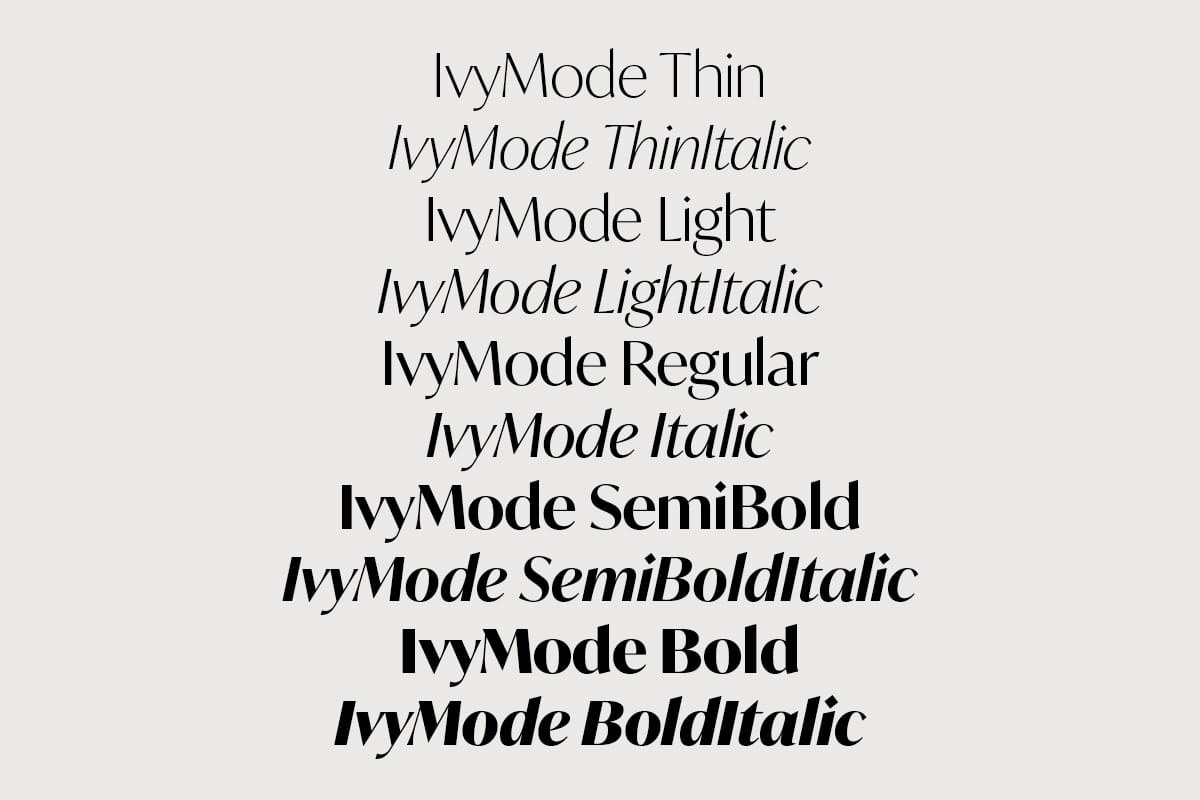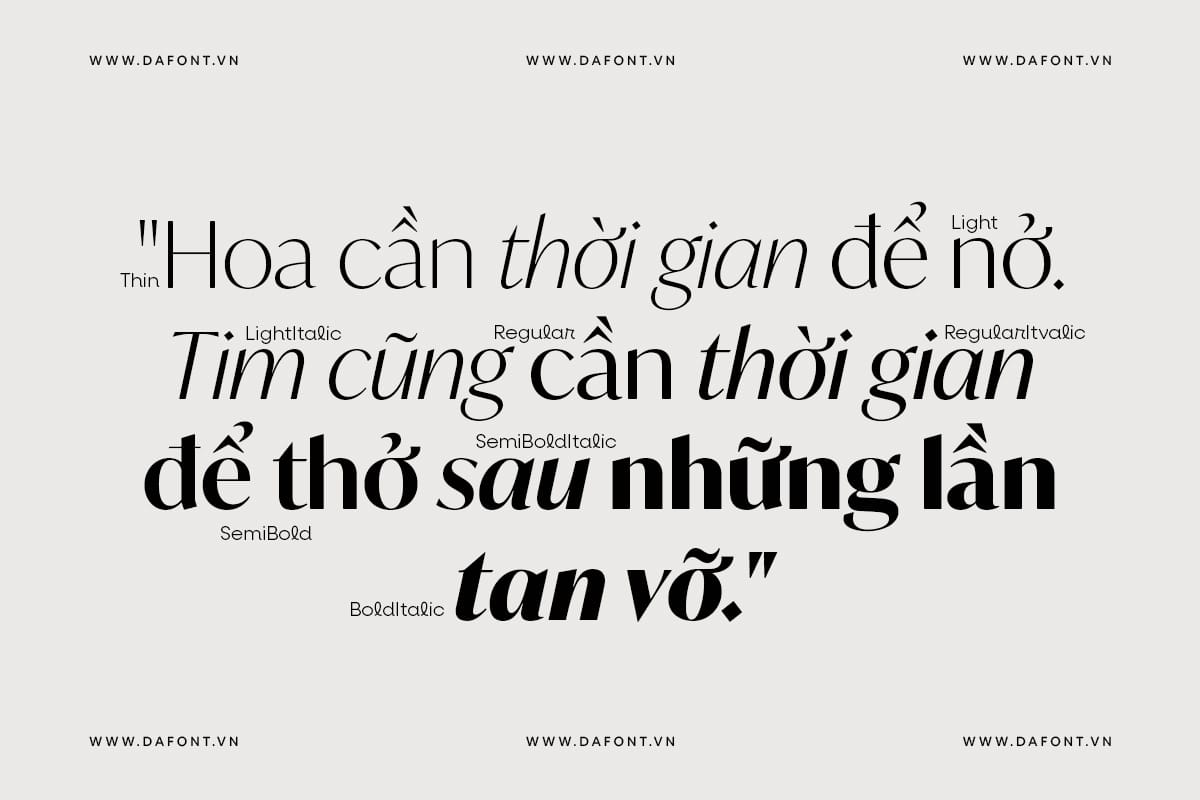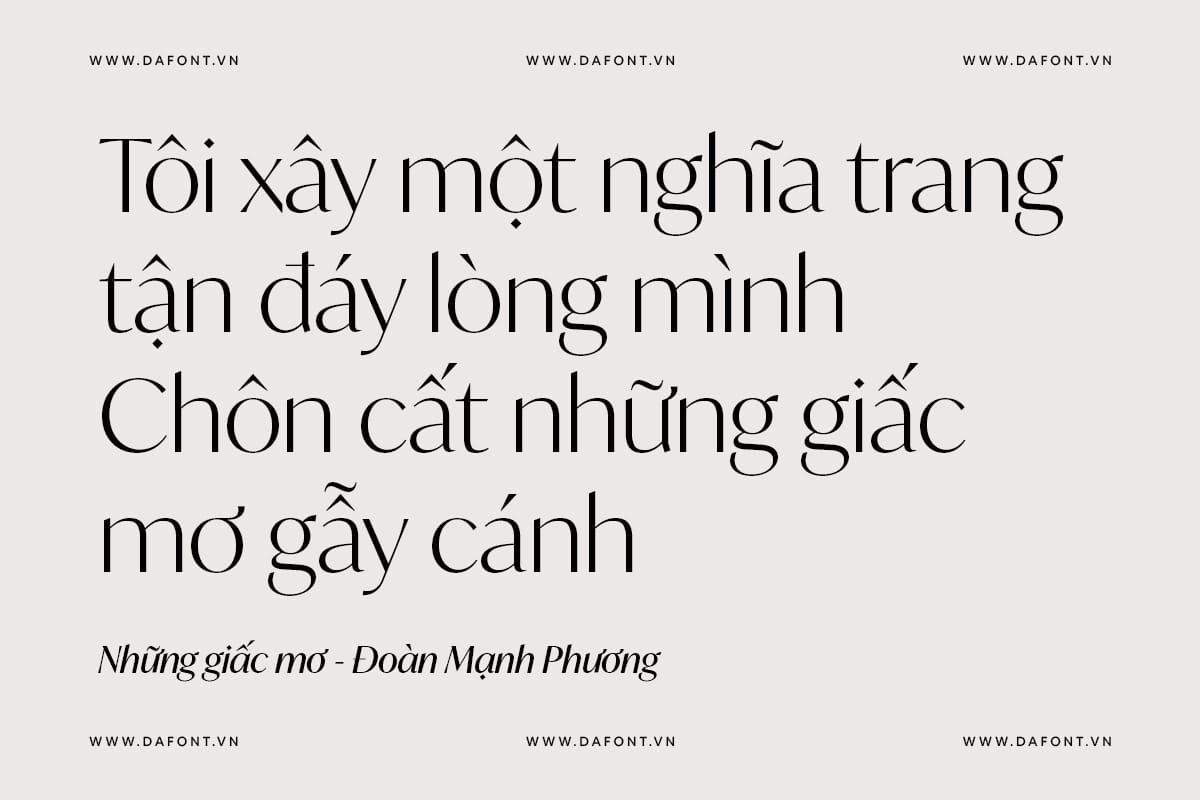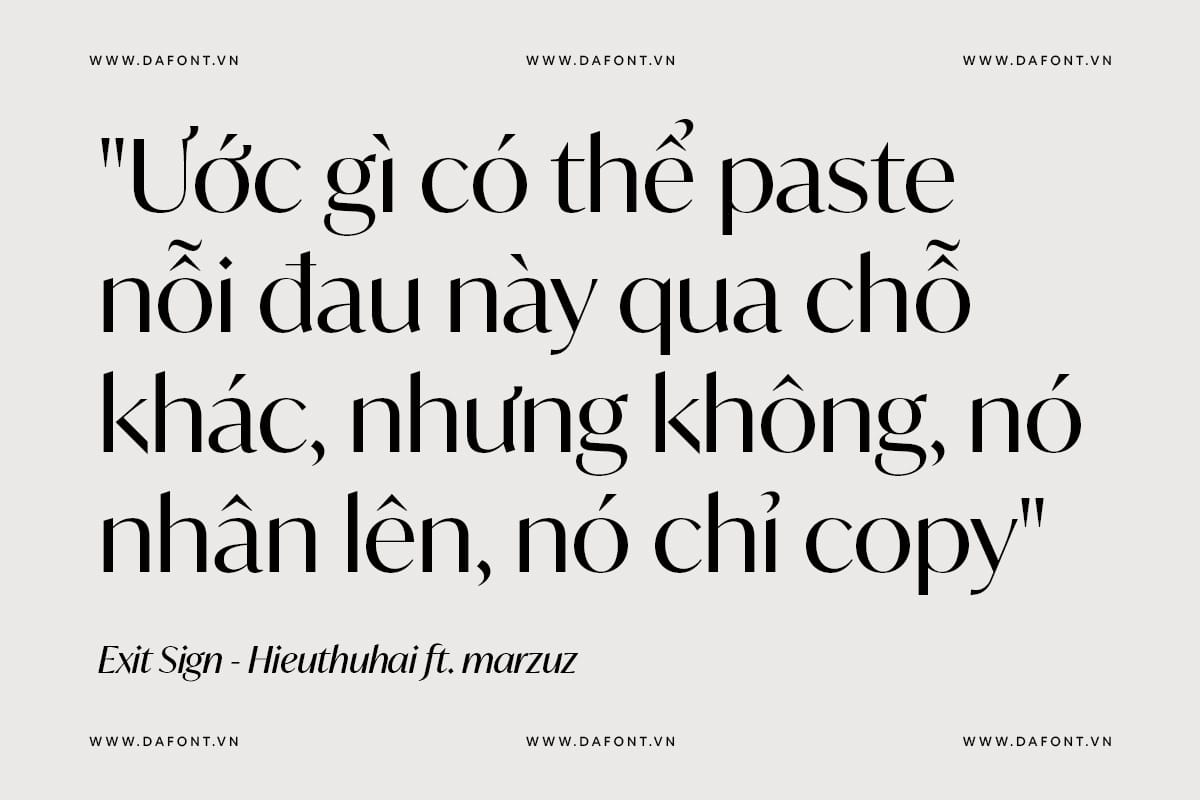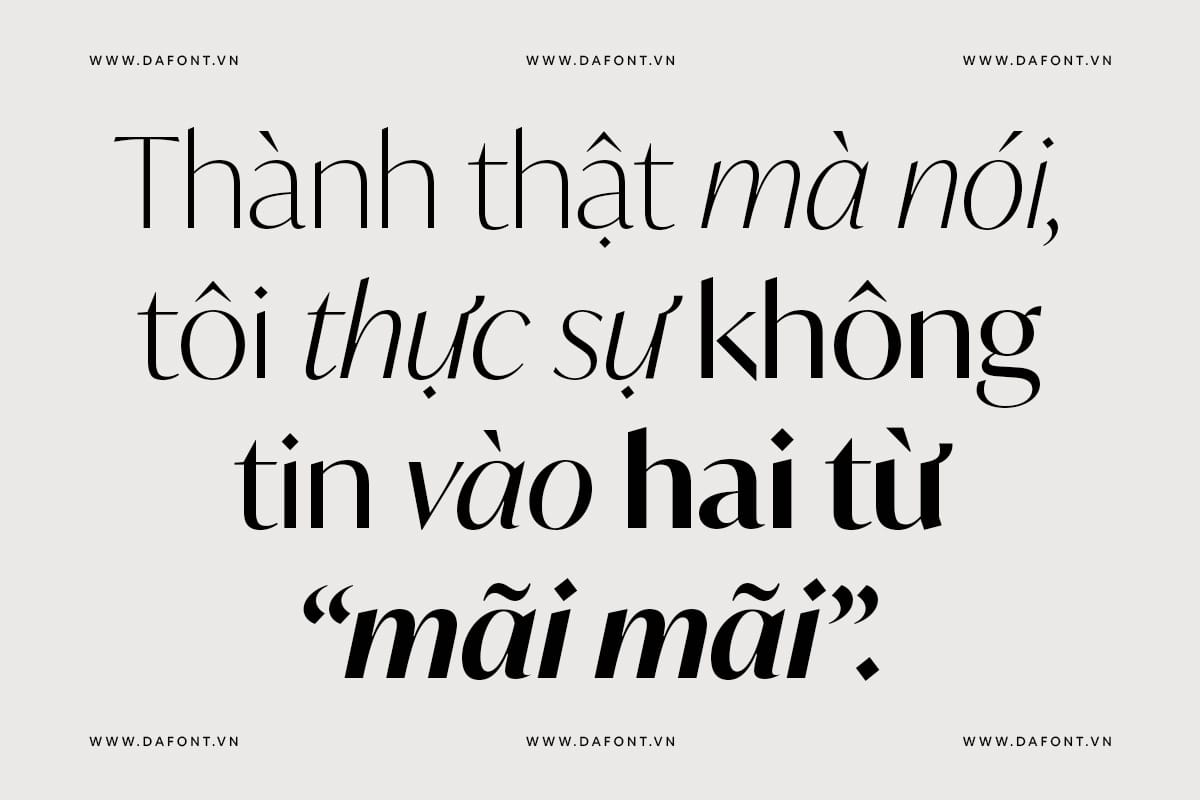
DFVN IvyMode việt hóa (10 font)
IvyMode được đặc trưng bởi độ tương phản mạnh mẽ và độ nghiêng vừa phải của nét chữ. Sự mở rộng ở các nét ngang cuối và các nét dọc mỏng, các nét lên và xuống cắt chéo, cùng với các chấm và dấu câu hình kim cương mang lại cho phông chữ sự sắc nét nhất định.
Các đỉnh và góc nhọn trên các chữ A, M, N, V và W cũng như các nét chéo kéo dài ra ngoài thân trái ở các chữ M và N tăng thêm độ sắc sảo cho nó. Bộ font này phù hợp để sử dụng làm kiểu chữ hiển thị phù hợp cho các thiết kế làm tiêu đề, logo, tạp chí, thời trang, xây dựng thương hiệu…
Nhà thiết kế: Jan Maack
DFVN IvyMode Font Family Preview